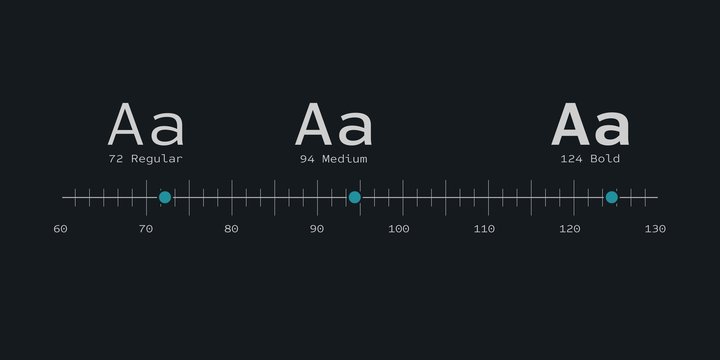
Myfonts Best Choice Font
[Myfonts] Best Choice Font
Best Choice - это семейство моноширинных шрифтов нового поколения для разработки, программирования, кодирования и верстки таблиц.